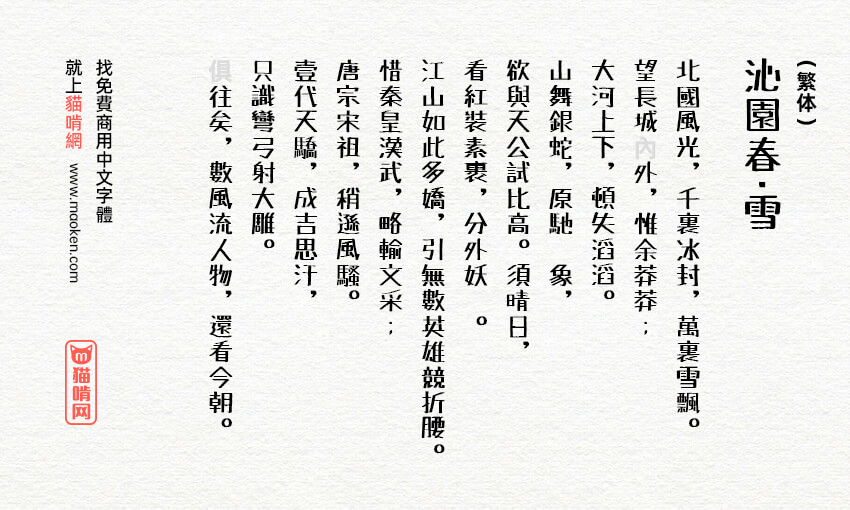
记得以前电脑还没有普及的时候,如果要画黑板报、制作海报等都会透过手写。很多人能拿马克笔写一套很动感又吸引注意力的艺术字体。早期也有不少教人写POP字形的书,不过我倒是没有涉猎,一直很佩服能写出这种字型的人。如果你跟我一样不会写POP字形又希望能够使用类似效果,那就赶紧下载这套字体吧。
马克笔手绘体(日文名:たぬき油性マジック,英文名:TanukiMagic)是一款日本网站提供的免费商用字型。这款字体横细竖粗,手写POP的感觉很有冲击力。字母的设计既有粗体线条的力量,又有宽敞的柔和,特别适合做促销类的海报设计。